Eccoci arrivati al quarto appuntamento con la nostra rubrica “Tipografia Mania” dove condividiamo con tutti voi delle fantastiche illustrazioni e grafiche che vedono come protagonisti principali i caratteri. Esempi fantastici e creazioni creative che vengono realizzate mescolando l’estro e l’arte tipografica. Font stravolti da mani esperte in manipolazione di immagini per dare ancora piu’ efficacia e forza al messaggio che vogliamo trasmettere al nostro utente. Godiamoci insieme questa raccolta di illustrazioni tipografiche, cercando nuovi stimoli che possono ispirare il nostro estro tipografico. Buona visione!
Tipografia Mania
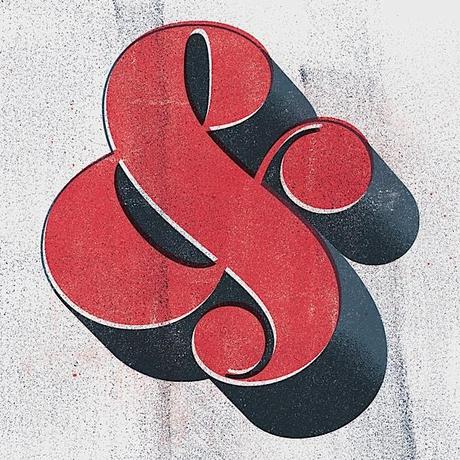
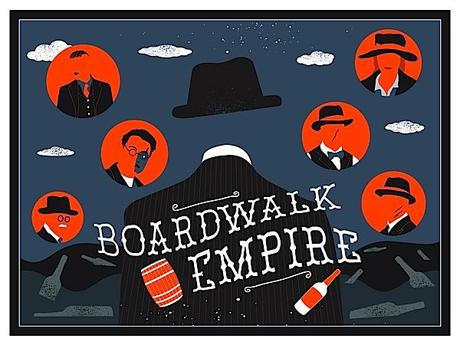
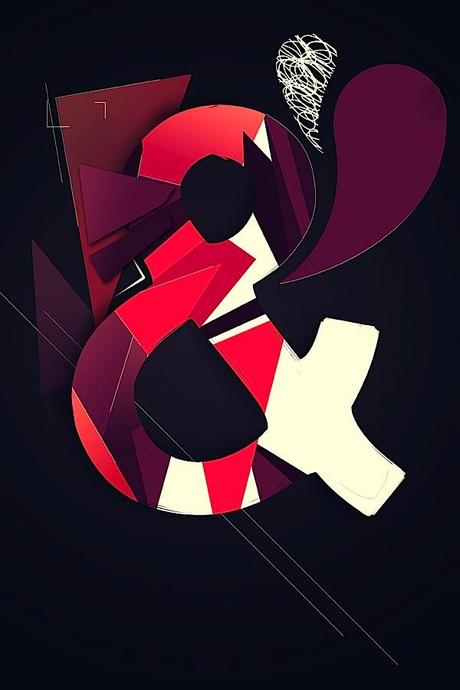
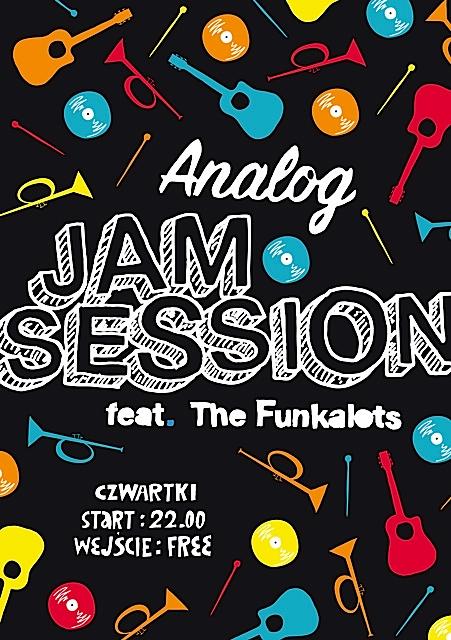
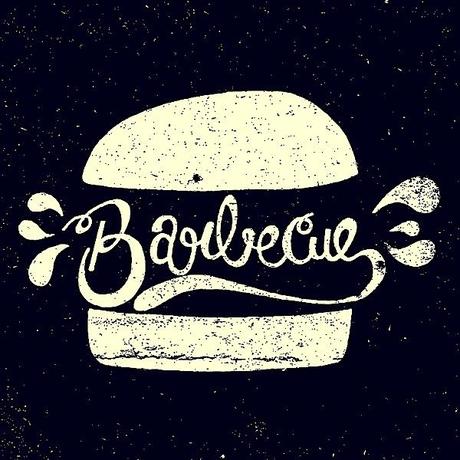
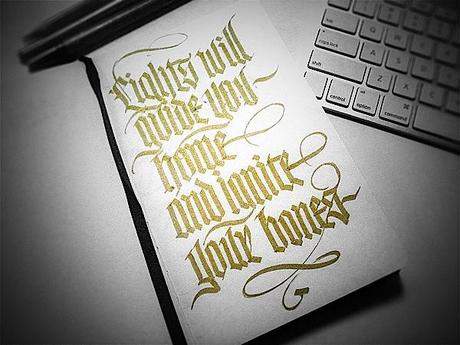
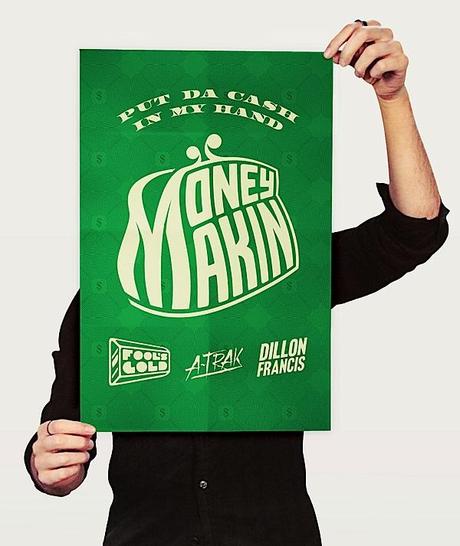
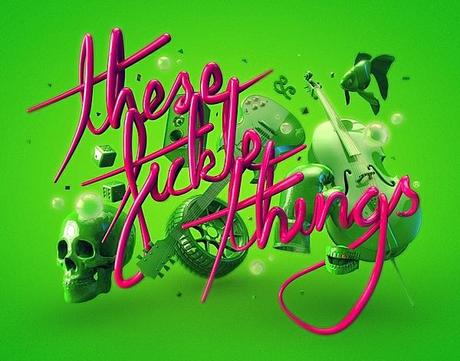
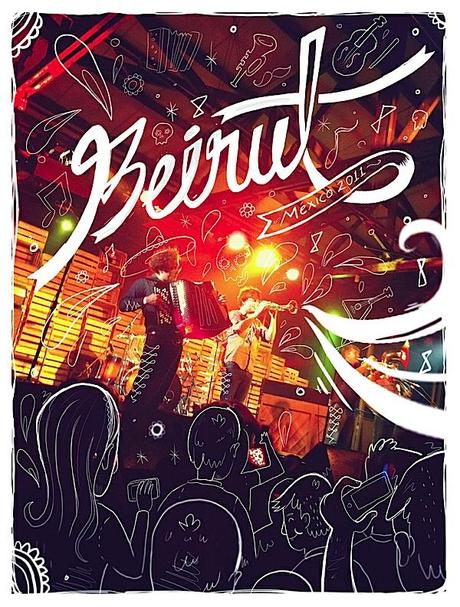
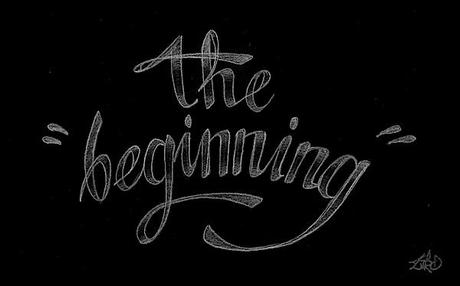
Conclusioni: